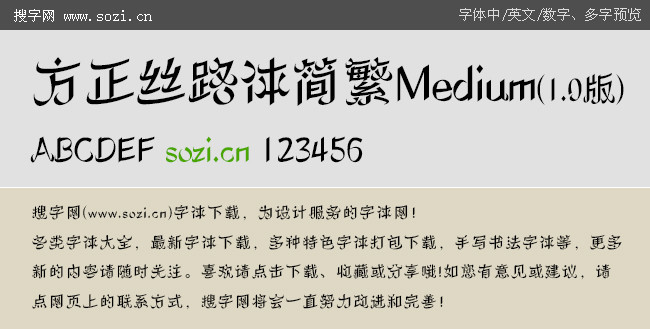
方正絲路體簡(jiǎn)繁Medium1.0
搜字網(wǎng)提供一款方正絲路體簡(jiǎn)繁Light1.0中文字體下載,方正絲路體在筆畫(huà)方面,有著自己特有的造型特征,撇和捺的折筆處、收尾處,需要靈活掌握幅度、大小,這些都會(huì)影響整個(gè)字的氣質(zhì)與態(tài)勢(shì);還有豎筆、撇筆,在筆畫(huà)橫豎交叉的地方做了氣口的處理,能夠適用于藝術(shù)設(shè)計(jì)、包裝印刷、簽名設(shè)計(jì)、圖形設(shè)計(jì)等應(yīng)用。(本字體為個(gè)人非商用版,如需要商用請(qǐng)聯(lián)系方正公司購(gòu)買(mǎi)版權(quán))
- 風(fēng)格類(lèi)別: 現(xiàn)代藝術(shù)體